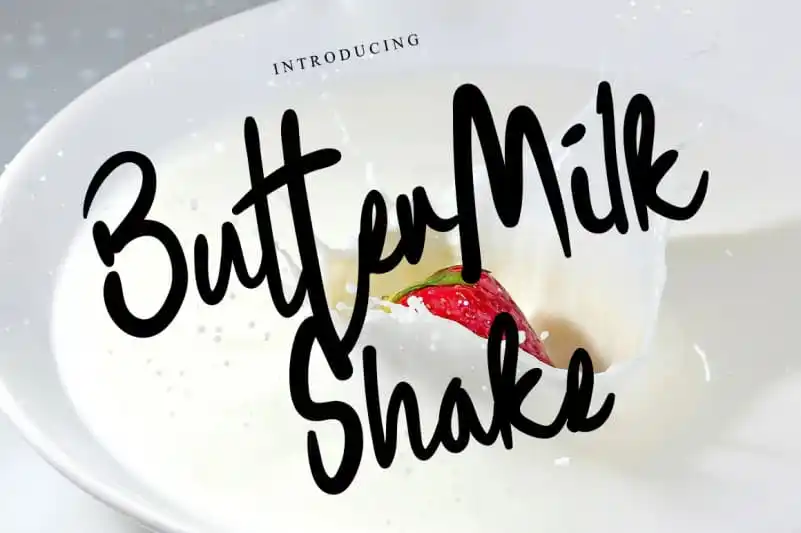
Buttermilk Shake Script Font – Download Grátis
A Buttermilk Shake Script Font é uma fonte escrita a mão delicada, fina e cursiva, criada por LevinCreative. Esta elegante fonte brilhará em uma variedade de ideias de design. Ela adicionará um toque descontraído e romântico a cada projeto que você criar. Perfeita para adicionar um toque único e encantador à sua arte digital, seja ela para cartazes, editoriais ou até mesmo para pequenos detalhes como títulos em sites pessoais. Engane-se ao pensar nela apenas como uma fonte; a Buttermilk Shake Script traz vida e personalidade aos seus designs digitais. Seja qual for o seu projeto, essa fonte será sua nova companheira de trabalho favorita para criar um design agradável e encantador.